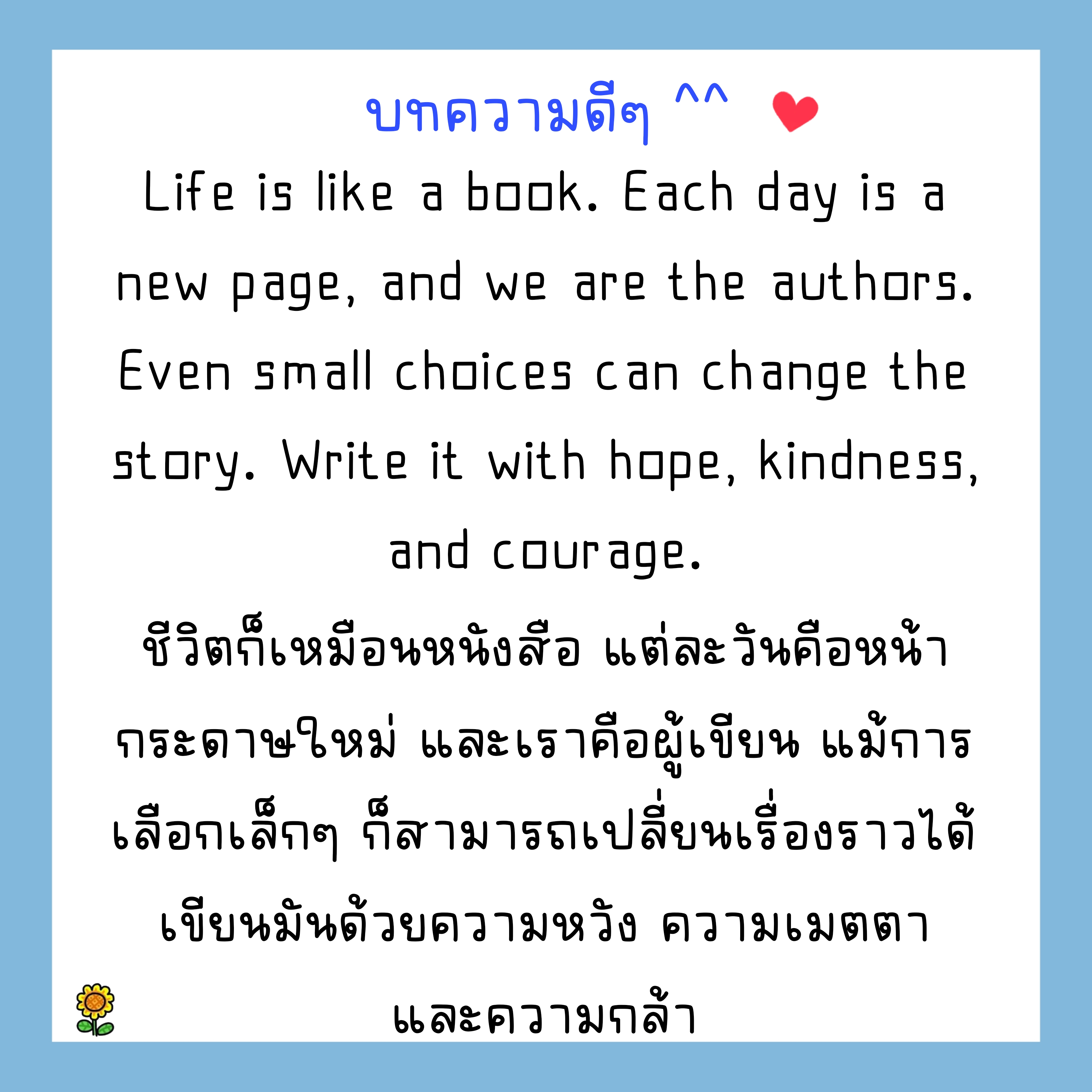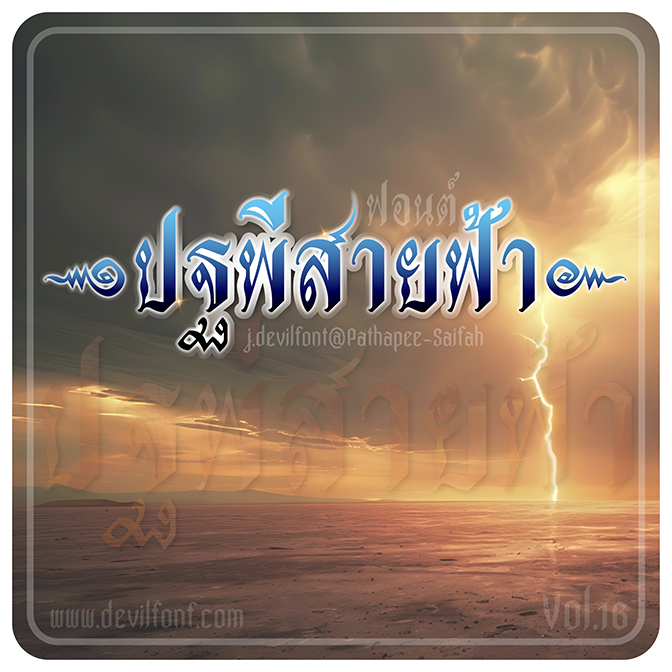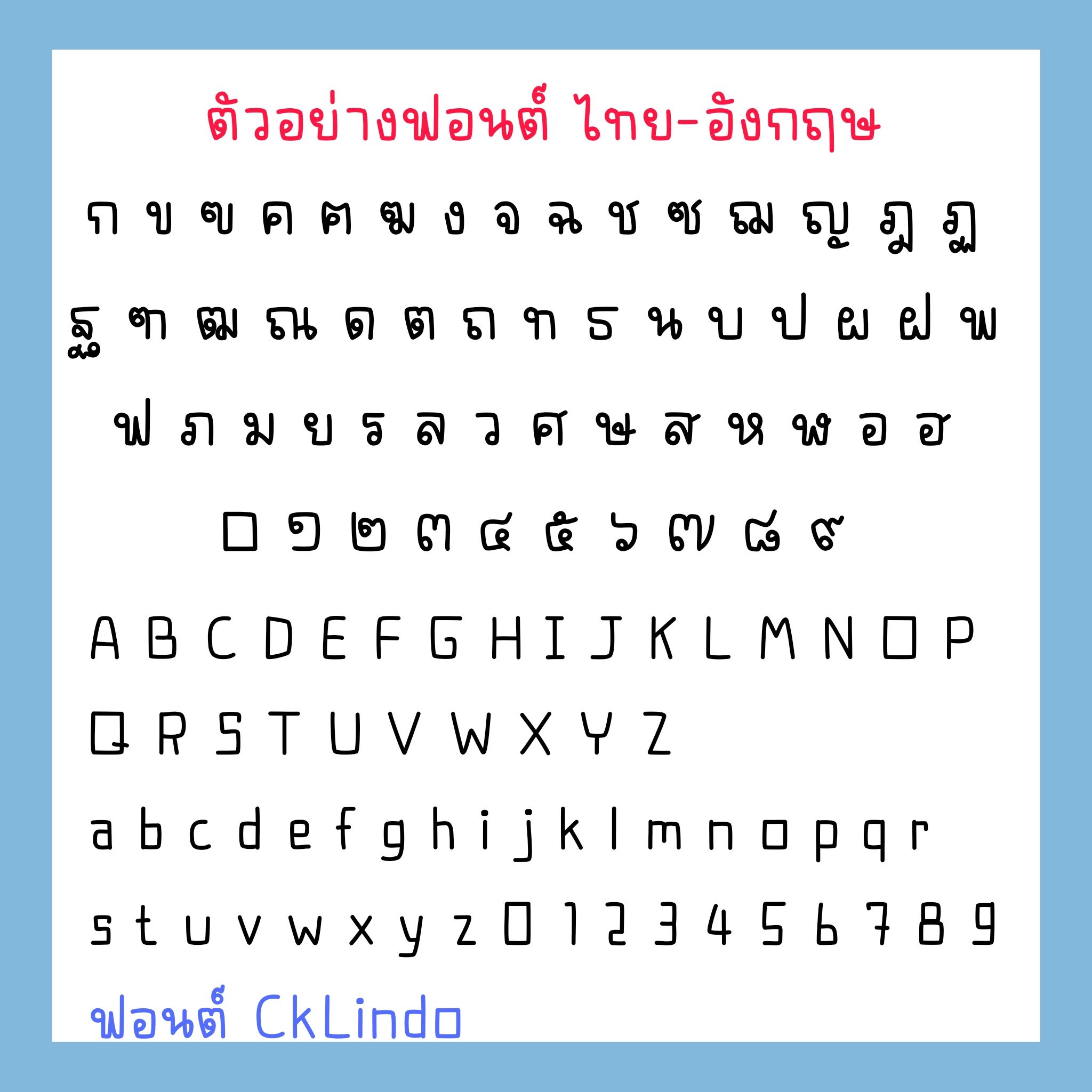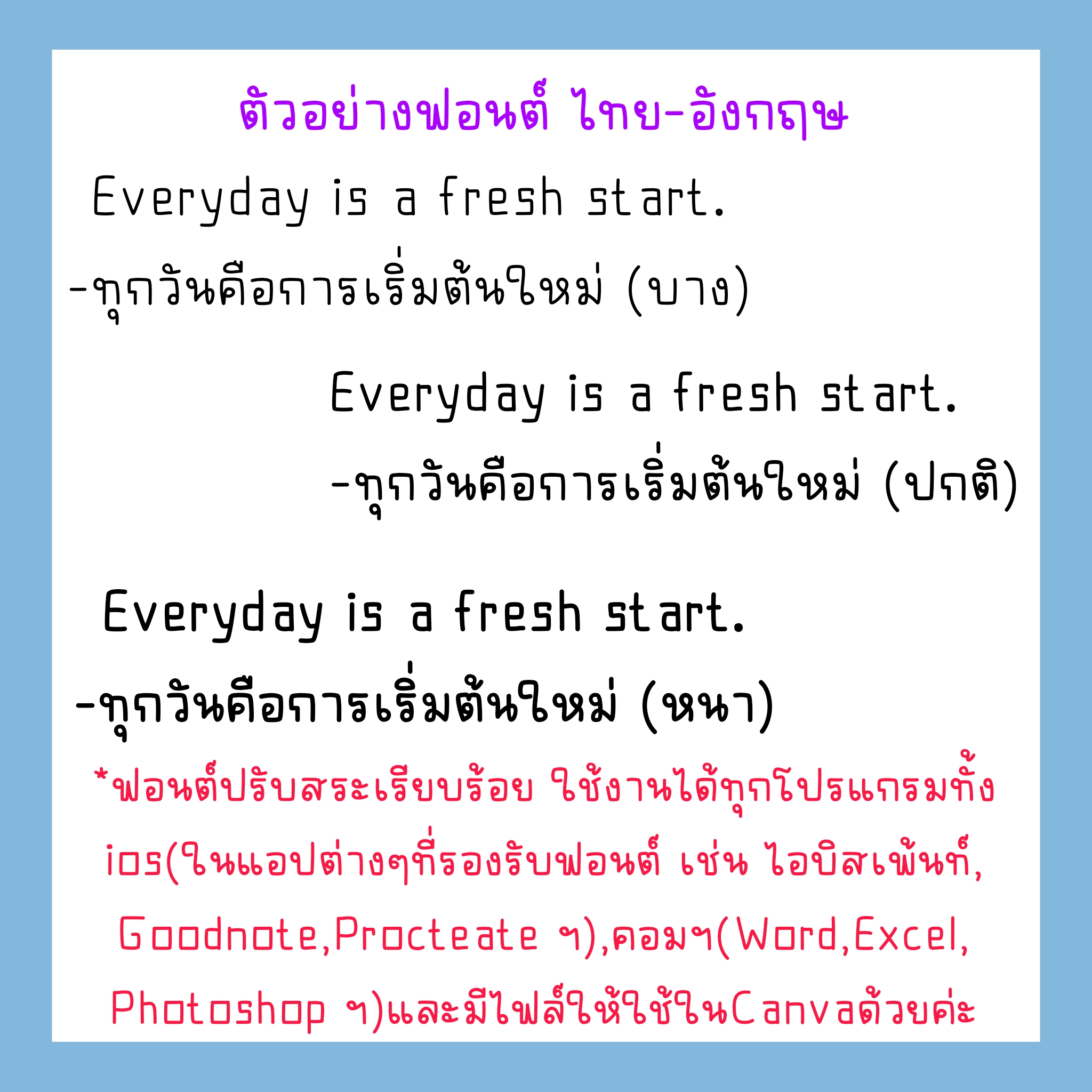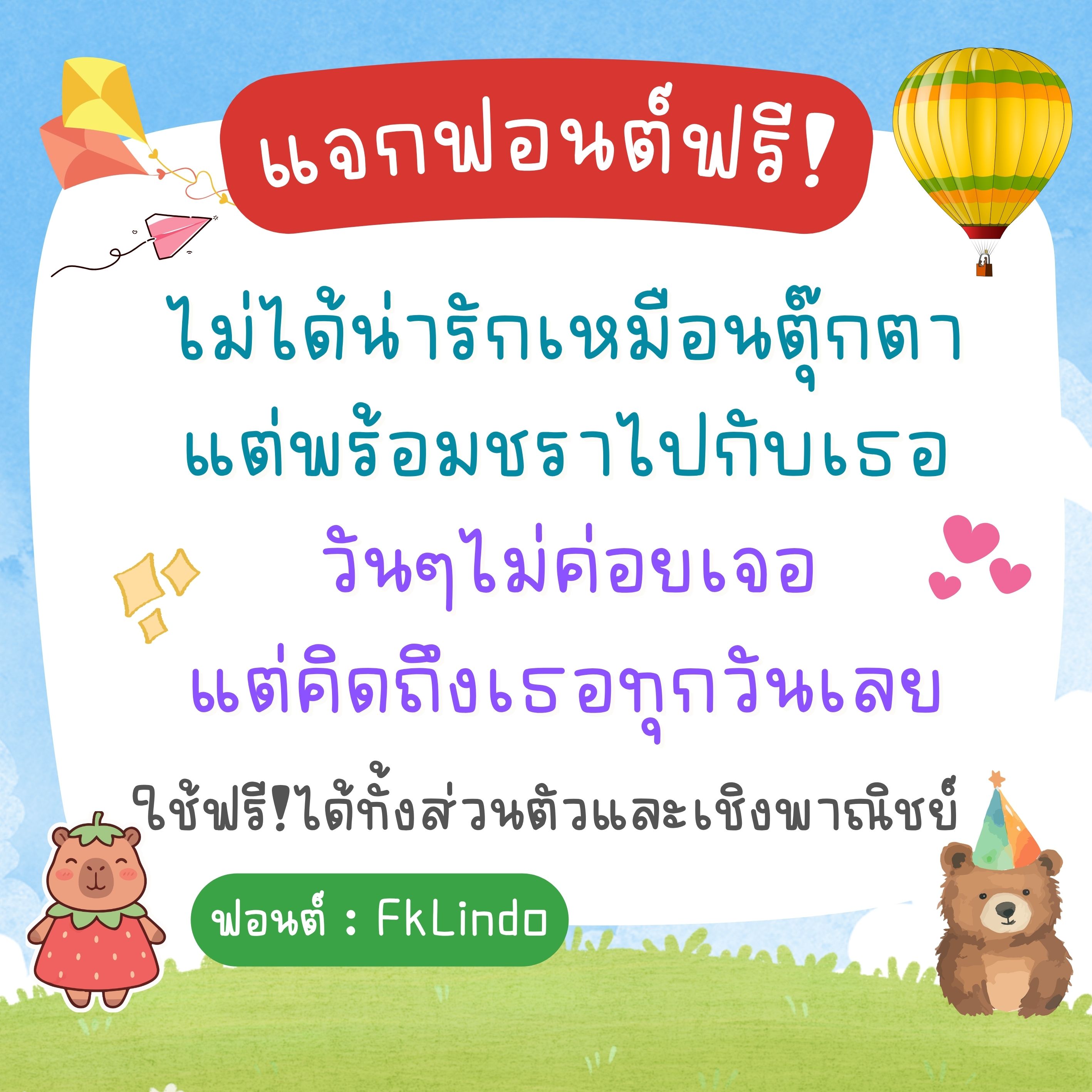
ฟอนต์ตัวที่ 16 ปฐพี-สายฟ้า
เปิดตัวฟอนต์วันที่ 25 เมษายน 2569
ชื่อ : สึคาว่า (GMCtsuCawaa)
ฟอนต์ทับทิมกรอบ [RDTubtimkrob]
แจกฟอนต์จ้า ^^
แจกฟอนต์จ้า!! ฟอนต์ FkLindo ฟอนต์ลายมือแนวตัวกึ่งเหลี่ยม น่ารัก
ฟอนต์ยำปลาดุกฟู [RDYampladookfoo]